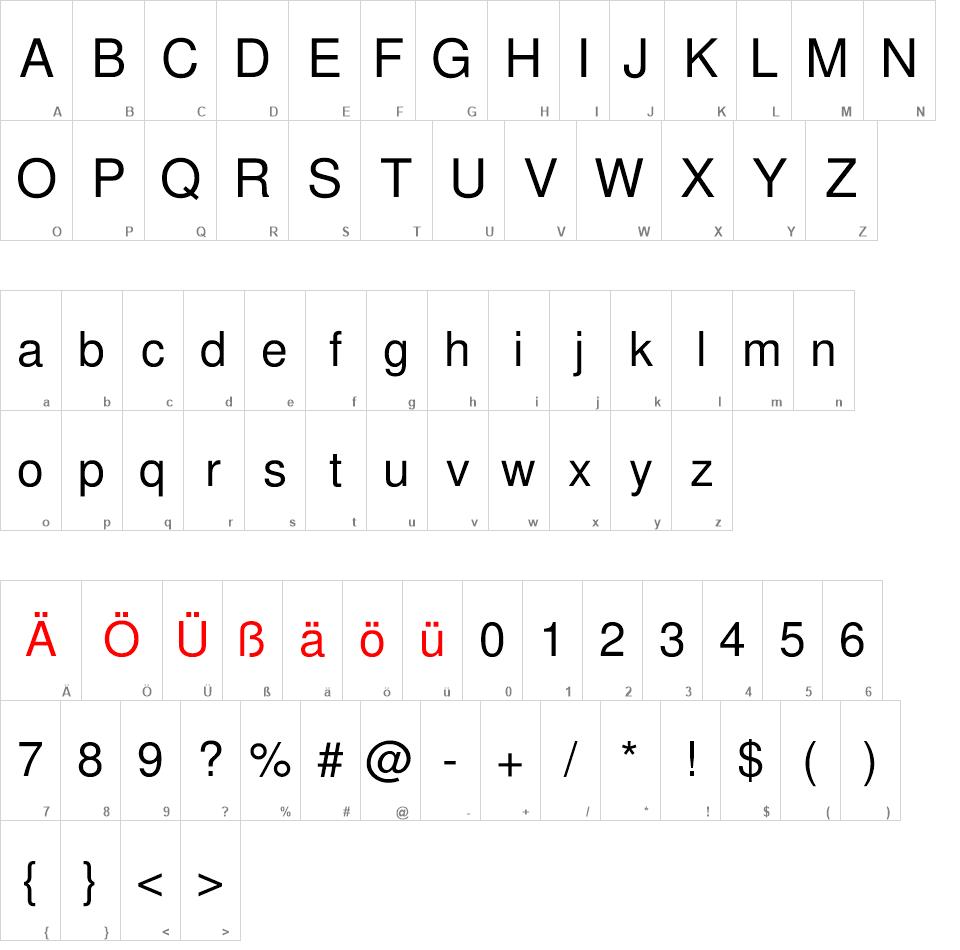
Nimbus Sans L Font Family
Nimbus Sans L ist eine Version von Nimbus Sans, die Adobe-Schriftquellen verwendet. Entwurf im Jahr 1987. Die Familie umfasst 17 Schriftarten mit 5 Gewichten und 2 Breiten; Nimbus Sans L Extra Black ist nur in komprimiertem Format erhältlich.
Eine Untergruppe von Nimbus Sans L, die reguläre und dunkle Schriftarten in allen Breiten und Stilen umfasst, wird in GPL und AFPL in LPPL, 1996 im Type 1-Format und 2009 veröffentlicht und ist eine der frei lizenzierten Schriftarten von URW ++.
Obwohl die Charaktere nicht genau gleich sind, hat Nimbus fast die gleichen Kriterien wie Sans L, Helvetica und Arial. Nimbus Sans L gehört zu einer Reihe kostenloser alternativer Ghostscript-Schriften, die für 35 einfache PostScript-Schriften (einschließlich Helvetica) verwendet werden.
Es ist eine Standardschrift in vielen GNU / Linux-Distributionen. OpenOffice.org wurde in einigen GNU / Linux-Distributionen in Calc und Impress als Standardschrift verwendet (z. B. Ubuntu - 8.10, bis die Standardschrift seit Ubuntu 9.04 in Salvation Sans geändert wurde).